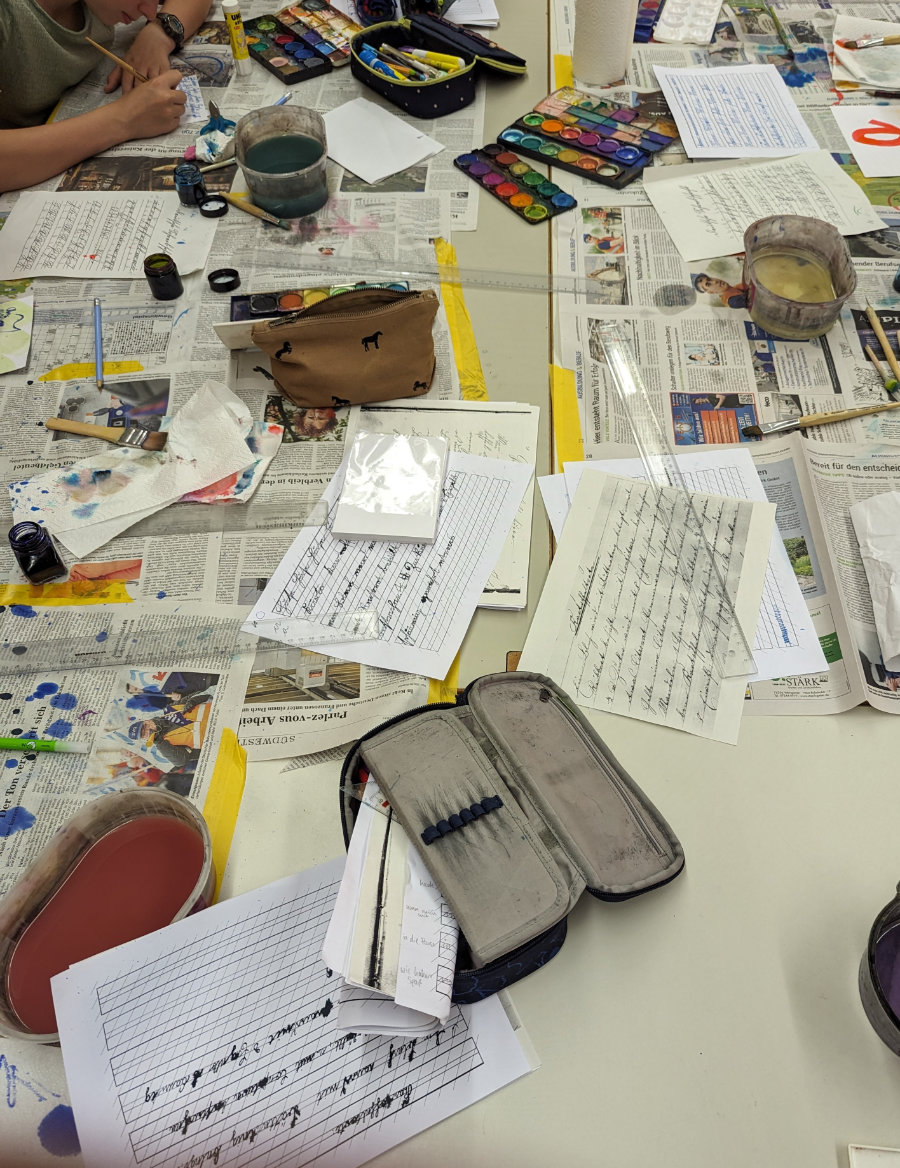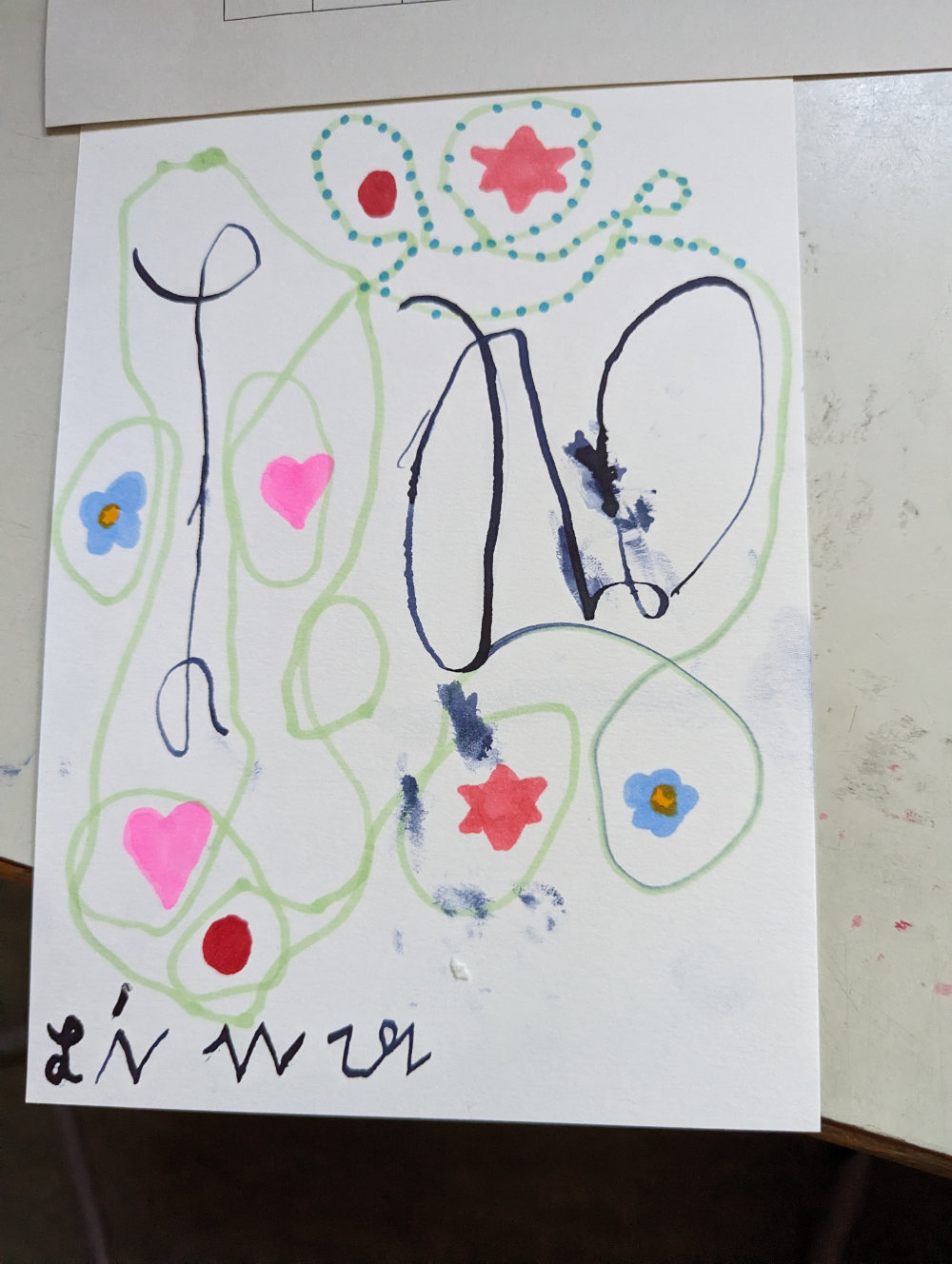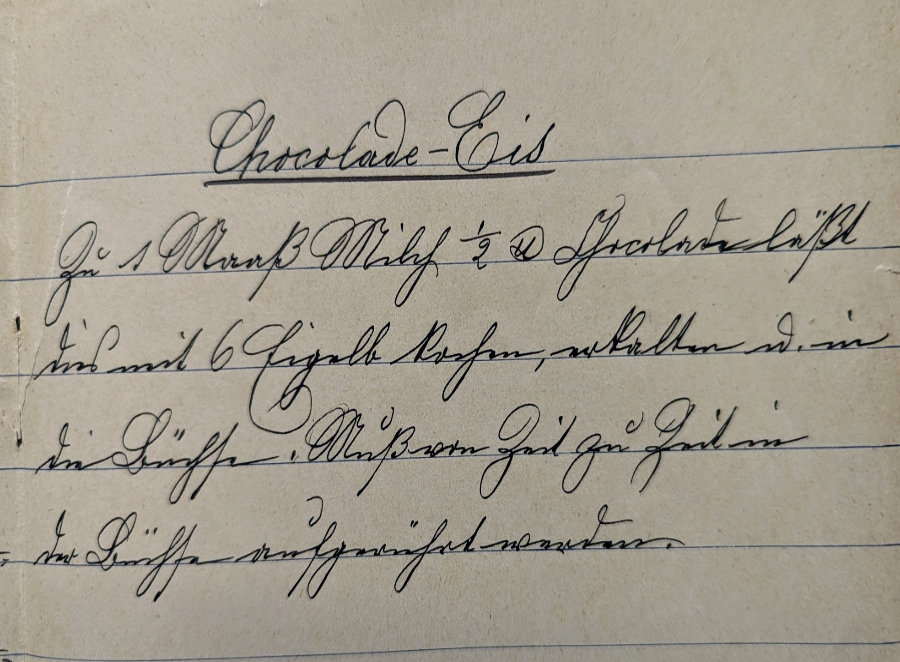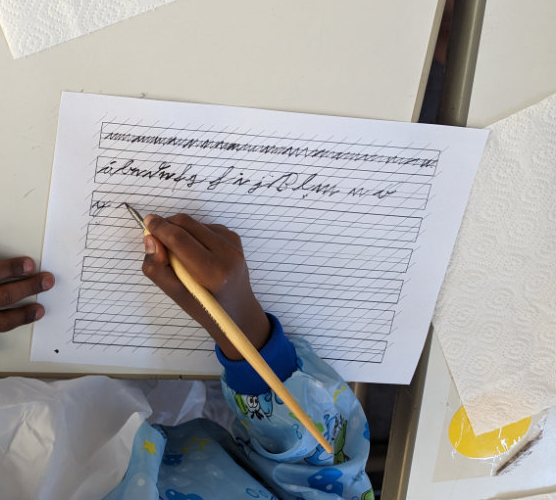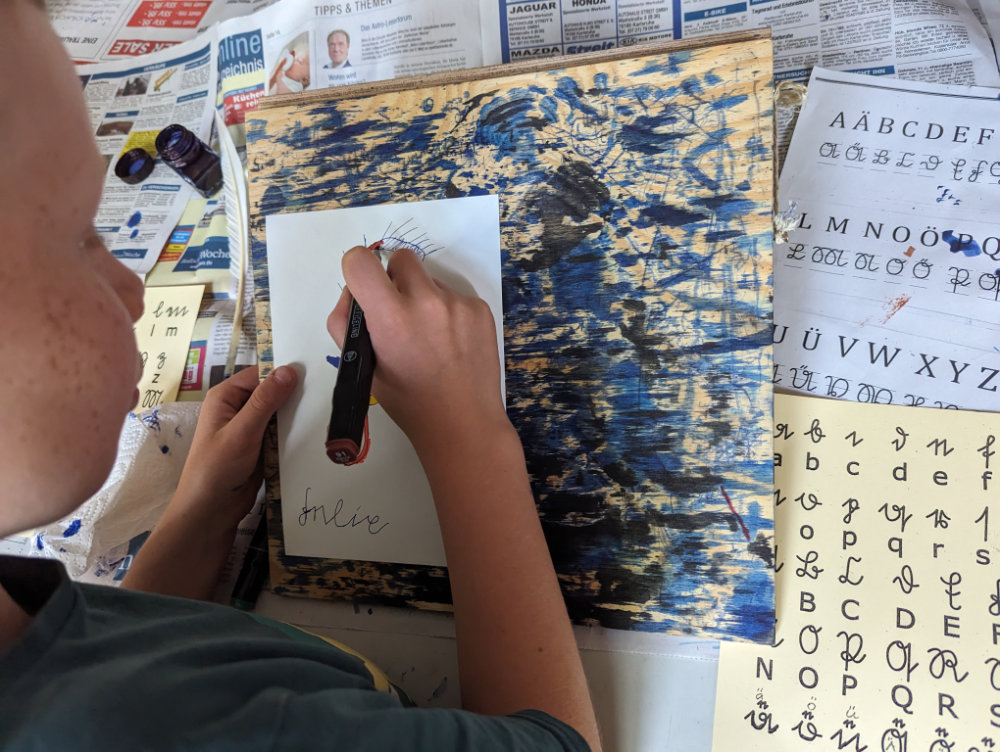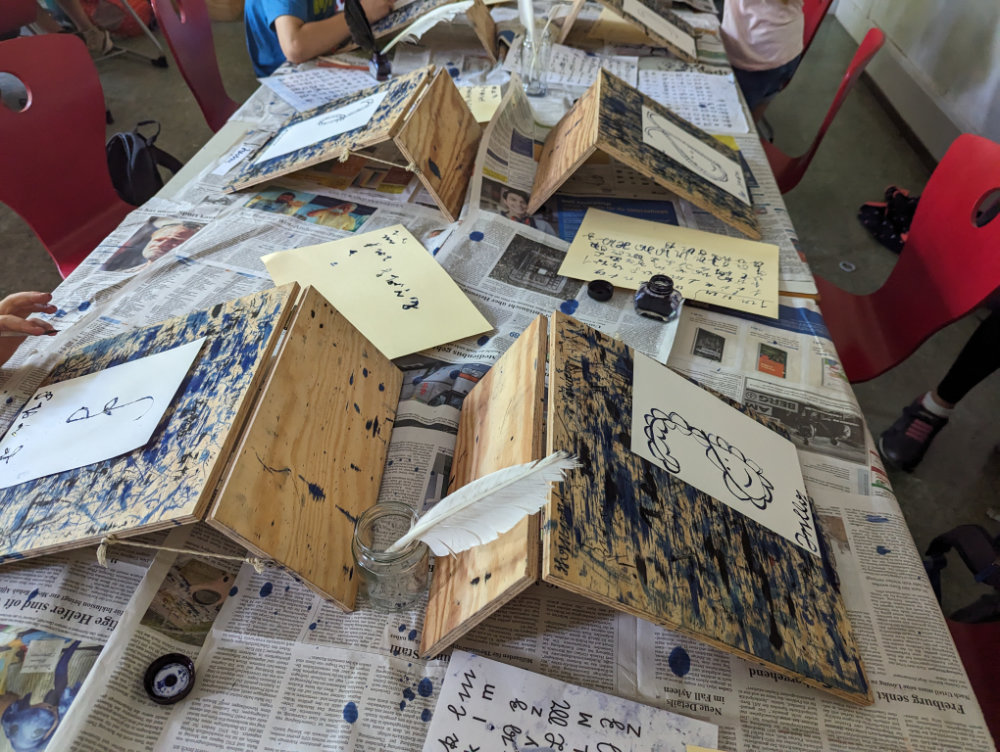
Schriften alter Schule
Schriftformen und Werkzeuge
Die Entwicklung der Schrift ist immer geprägt durch die unterschiedlichen kulturellen Strömungen, durch das verfügbare Schreibmaterial und die notwendigen Schreibwerkzeuge.
Unsere sogenannte lateinische Schrift geht zurück auf die alten Römer. Da waren zunächst die Majuskeln (große Buchstaben – bei uns heute Blockschrift genannt). Sie hatten die Funktion die Macht und den Reichtum des Römischen Reiches auszudrücken. Sie wurde zunächst in Stein gehauen. Material und Werkzeuge also Stein, Hammer und Meißel. Die Schriftform heißt ANTIQUA.
Im 8. Jahrhundert wurde durch Karl der Große die Minuskeln in Europa verbreitet. Auch hier eine Herrschaftsschrift. Durch die Kombination aus Groß- und Kleinbuchstaben wurde die Lesbarkeit erleichtert.
Auf beides geht unsere heutige Schreibweise aus Groß- und Kleinbuchstaben mit der sog. lateinischen Schrift zurück. Sie entstand als Schreibschrift um 1600 vor allem in Frankreich und England.
Zur gleichen Zeit etablierte sich ab dem 16. Jahrhundert die Currentschrift – auch deutsche Schrift genannt - als die übliche Amts- und Verwaltungsschrift im gesamten deutschen Sprachraum. Sie war ursprünglich eine Kanzleischrift. Nach Erfindung der Stahlfeder / Spitzfeder veränderte sie sich in ihrer Form. Sie wurde in Preußen als Schulschrift eingeführt. Und blieb mit der Vereinfachung durch Sütterlin bis zum Verbot durch die Nazis bis 1941 übliche Schreibschrift.
Ab 1850 wurde der Füllfederhalter industriell hergestellt und verdrängte den einfachen Federhalter mit der Spitzfeder allmählich. Schreiben mit einer gleichmäßig fließenden Tinte erleichterte das Schreiben – und man sparte einfach Zeit.
Deutsche Schrift in der Südstadtschule Pforzheim
25 Schüler*innen von Klasse 2 bis 6 der Südstadtschule in Pforzheim haben sich für das Projekt "Deutsche Schrift lernen" entschieden. Einen ganzen Vormittag sind sie konzentriert bei der Sache, üben die neuen Buchstaben zunächst mit Bleistift und Linienblatt. Dann wechseln wir zu Federhalter und Stahlfeder. Es ist erstaunlich wie schnell und fasziniert sie von dser alten Schrift sind. Ein autistischer Schüler schreibt seitdem sein Tagebuch in Deutscher Schrift.
Sütterlin Schrift in der Riedschule Karlsruhe-Rüppurr
Eine ganze Woche erfahren die Schüler*innen von der 1. bis 4. Klasse der Riedschule in Rüppurr, welche Handwerksarbeiten es zur Gründung Karlsruhe 1715 gab. Fachwerkbau, Seileerei, Papierschöpfen und noch mehr.
Ein Projekt: die Schreibstube. Mit Vogelfeder und Tinte übten sich die Schüler*innen in der Sütterlin-Schrift. Für die kurze Zeit eine Herausforderung: erst die Buchstaben üben und dann ein Initial mit Verzierung schreiben, zum Schluss noch der Eintrag ins Bürgerbuch. Natürlich gab es viele Tintenkleckse und blaue Finger. Trotzdem viel Begeisterung.
Deutsche Schrift am Albertus-Magnus-Gymnasium Ettlingen
25 Schülerinnen und Schüler melden sich bei den Projekttagen im AMG für die Beschäftigung mit Schrift. Erster Tag war Brushlettering angesagt (habe ich leider nicht erlebt). Am zweiten Tag "Deutsche Schrift" - aus dem einen Tag wurden dann gleich mindestens zwei.
Angefangen mit der Herausforderung: Enträtseln eines handgeschriebenen Rezeptes aus einem alten Rezeptbuch. Mit Buchstabenblatt arbeiten stifsich die Schüler*innen Zeichen für Zeichen vor und entwickeln die Lust auf diese seltsame Schrift. Schreiben schreiben - zuerst mit Bleistift und Linieblatt, dass mit Federhalter, Spitzfeder und Tinte.
Der zweite Tag dann große Initialen mit Verzierungen, dann eine Postkarte an Opa oder Oma. "Aber die Adresse muss ich dann in unserer normale Schrift schreiben, sonst kann es der Briefträger doch nicht lesen!" der Kommentag einer Schülerin.
Alle sind konzentriert, neugierig und begeistert. Fast ohne Pause zwei ganze Vormittage.